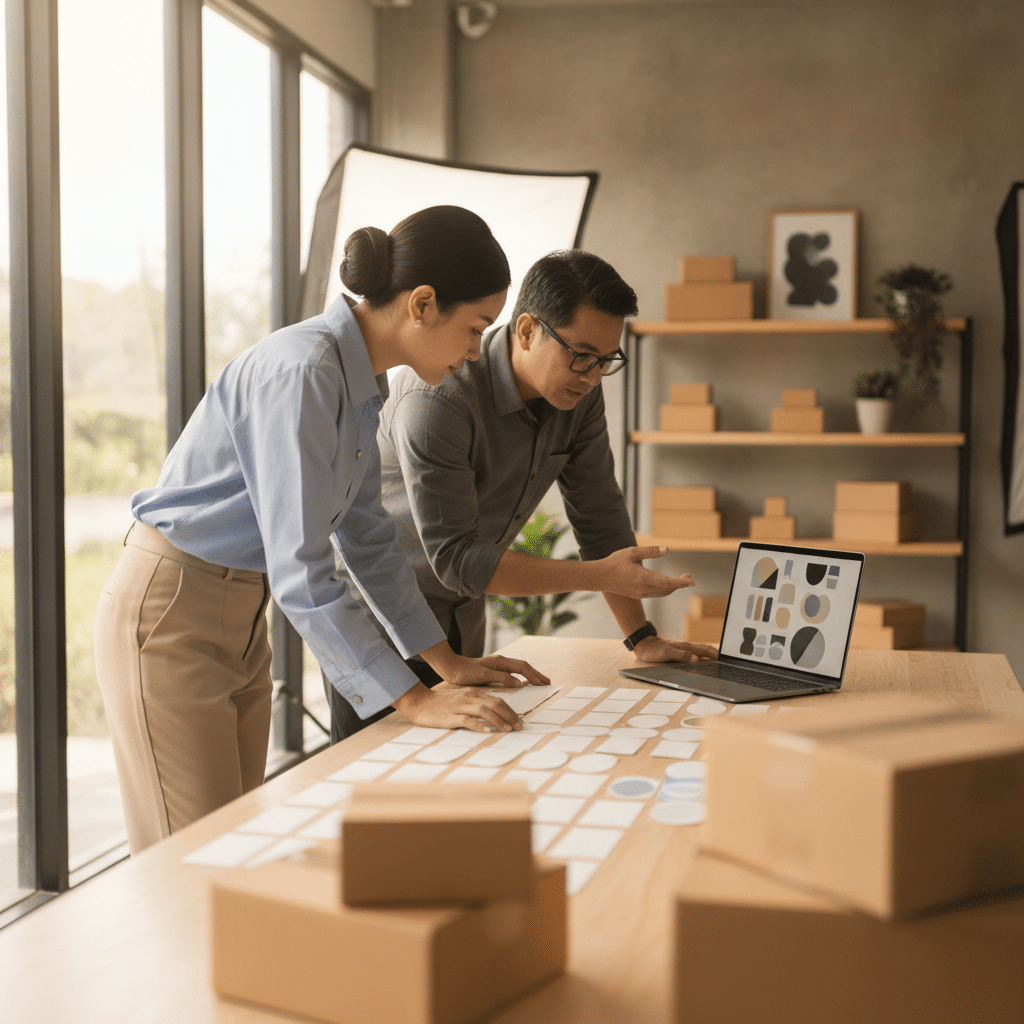
ทริคเลือกฟอนต์ฉลากสินค้า สะกดสายตา เพิ่มยอดขายปัง!
การเรียนรู้ทริคเลือกฟอนต์ฉลากสินค้า สะกดสายตา เพิ่มยอดขายปัง! เป็นมากกว่าการเลือกตัวอักษรที่สวยงาม แต่คือกลยุทธ์สำคัญในการสร้างแบรนด์และสื่อสารกับลูกค้าโดยตรง ฟอนต์ที่เหมาะสมสามารถสร้างความประทับใจแรกเห็น ดึงดูดความสนใจบนชั้นวางสินค้า และสื่อถึงคุณภาพและตัวตนของผลิตภัณฑ์ได้อย่างมีประสิทธิภาพ การเลือกฟอนต์จึงเป็นองค์ประกอบที่ผู้ประกอบการไม่ควรมองข้ามในการออกแบบฉลากสินค้าและบรรจุภัณฑ์
หัวใจสำคัญของการเลือกฟอนต์บนฉลากสินค้า
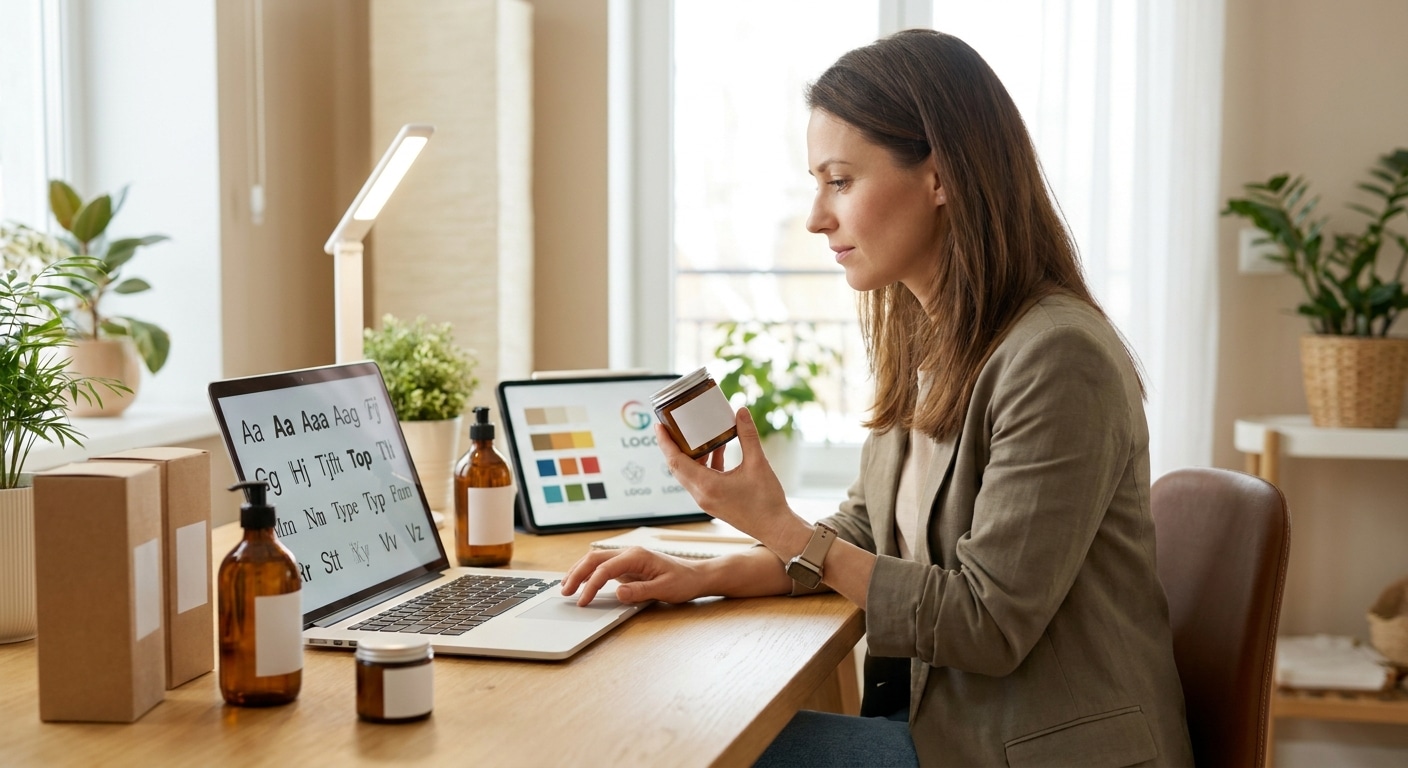
การเลือกฟอนต์สำหรับฉลากสินค้าที่มีประสิทธิภาพนั้นตั้งอยู่บนหลักการสำคัญที่ส่งผลโดยตรงต่อการรับรู้ของผู้บริโภคและการตัดสินใจซื้อ หลักการเหล่านี้ช่วยให้แน่ใจว่าฉลากไม่เพียงแต่สวยงาม แต่ยังทำหน้าที่สื่อสารได้อย่างสมบูรณ์
- ความชัดเจนในการอ่าน (Readability): ฟอนต์ต้องอ่านง่ายในทุกสถานการณ์ ไม่ว่าจะมองจากระยะไกล บนชั้นวาง หรือบนพื้นที่ขนาดเล็กของฉลาก ข้อมูลสำคัญ เช่น ชื่อสินค้า ส่วนประกอบ และวันหมดอายุ ต้องชัดเจนที่สุด
- การสะท้อนบุคลิกแบรนด์ (Brand Alignment): รูปแบบของฟอนต์ต้องสอดคล้องกับภาพลักษณ์ของแบรนด์ สินค้าพรีเมียมควรใช้ฟอนต์ที่ดูหรูหรา ในขณะที่สินค้าสำหรับเด็กควรใช้ฟอนต์ที่ดูสนุกสนานและเป็นมิตร
- ความเหมาะสมกับพื้นที่ (Space Suitability): การออกแบบต้องคำนึงถึงขนาดและรูปทรงของฉลาก ฟอนต์ที่เลือกต้องไม่ทำให้ฉลากดูอึดอัดหรือรกจนเกินไป และต้องจัดวางองค์ประกอบต่างๆ ได้อย่างลงตัว
- ความเรียบง่ายและเป็นระเบียบ (Simplicity): การใช้ฟอนต์จำนวนน้อยแบบ (ไม่เกิน 2-3 แบบ) จะช่วยให้ฉลากดูสะอาดตา เป็นมืออาชีพ และไม่สร้างความสับสนให้กับผู้บริโภค
ทำไมฟอนต์บนฉลากจึงมีผลต่อการตัดสินใจซื้อ
ในตลาดที่มีการแข่งขันสูง ฉลากสินค้าคือ “พนักงานขายเงียบ” ที่ทำงานตลอด 24 ชั่วโมง ฟอนต์ที่ใช้บนฉลากมีบทบาททางจิตวิทยาอย่างมากในการโน้มน้าวผู้บริโภค มันเป็นองค์ประกอบแรกๆ ที่สร้างการเชื่อมต่อทางอารมณ์และส่งผลต่อการรับรู้คุณค่าของผลิตภัณฑ์
การสื่อสารตัวตนของแบรนด์ในเสี้ยววินาที
ก่อนที่ลูกค้าจะได้อ่านข้อมูลทั้งหมดบนฉลาก พวกเขาจะรับรู้ถึง “ความรู้สึก” โดยรวมที่ฟอนต์สื่อออกมา ฟอนต์แบบ Sans-serif ที่เรียบง่ายและทันสมัยอาจสื่อถึงความน่าเชื่อถือ นวัตกรรม และความตรงไปตรงมา เหมาะสำหรับสินค้าเทคโนโลยีหรือผลิตภัณฑ์เพื่อสุขภาพ ในทางกลับกัน ฟอนต์แบบ Script ที่มีความโค้งมนสวยงามอาจสื่อถึงความหรูหรา ความเป็นงานฝีมือ หรือความเป็นธรรมชาติ เหมาะสำหรับสินค้าความงาม ไวน์ หรือสินค้าแฮนด์เมด การเลือกฟอนต์ที่ตรงกับแก่นแท้ของแบรนด์จะช่วยให้ลูกค้าเข้าใจตัวตนของสินค้าได้ทันทีและสร้างความรู้สึกเชื่อมโยงได้รวดเร็วยิ่งขึ้น
สร้างความน่าเชื่อถือและคุณภาพให้กับสินค้า
การออกแบบฉลากที่ดูเป็นมืออาชีพและอ่านง่ายจะสร้างความรู้สึกน่าเชื่อถือให้กับผู้บริโภค หากฉลากใช้ฟอนต์ที่อ่านยาก จัดวางไม่เป็นระเบียบ หรือดูไม่สอดคล้องกัน อาจทำให้ลูกค้ารู้สึกว่าผลิตภัณฑ์นั้นขาดความใส่ใจในรายละเอียดและอาจมีคุณภาพต่ำ การเลือกฟอนต์ที่เหมาะสมและการจัดวางองค์ประกอบอย่างมีหลักการจึงเป็นการลงทุนที่ช่วยยกระดับภาพลักษณ์ของสินค้าให้ดูมีคุณภาพและน่าไว้วางใจ ซึ่งเป็นปัจจัยสำคัญที่นำไปสู่การตัดสินใจซื้อในที่สุด
หลักการพื้นฐาน: เลือกฟอนต์อย่างไรให้ตอบโจทย์
การเลือกฟอนต์สำหรับฉลากสินค้าไม่ใช่เรื่องของความชอบส่วนตัว แต่เป็นกระบวนการที่ต้องอาศัยความเข้าใจในหลักการออกแบบและการสื่อสาร เพื่อให้ได้ผลลัพธ์ที่สามารถดึงดูดลูกค้าและสร้างยอดขายได้จริง
ความชัดเจนต้องมาก่อนความสวยงาม (Readability First)
หน้าที่หลักของข้อความบนฉลากคือการให้ข้อมูล ฟอนต์ที่สวยงามแต่ซับซ้อนจนอ่านยากอาจทำให้ลูกค้าพลาดข้อมูลสำคัญ เช่น คำเตือนการแพ้ ส่วนประกอบหลัก หรือวิธีการใช้งาน ซึ่งอาจส่งผลเสียต่อการตัดสินใจซื้อและประสบการณ์หลังการใช้งาน ควรทดสอบฟอนต์ในขนาดต่างๆ ที่จะใช้จริงบนฉลากเพื่อให้แน่ใจว่าสามารถอ่านได้อย่างชัดเจน แม้ในกลุ่มผู้บริโภคที่มีปัญหาสายตาหรือเมื่อมองผ่านๆ บนชั้นวางสินค้า
ความสอดคล้องกับบุคลิกของแบรนด์ (Brand Personality)
ฟอนต์เปรียบเสมือน “น้ำเสียง” ของแบรนด์ การเลือกใช้ฟอนต์จึงต้องสะท้อนบุคลิกที่แบรนด์ต้องการสื่อสารออกไปอย่างถูกต้อง
- แบรนด์หรูหรา/พรีเมียม: มักนิยมใช้ฟอนต์ประเภท Serif ที่มีเชิง ซึ่งให้ความรู้สึกคลาสสิก สง่างาม และน่าเชื่อถือ หรือฟอนต์ Sans-serif ที่บางและเรียบง่ายเพื่อสื่อถึงความมินิมอลและทันสมัย
- แบรนด์สำหรับเด็ก/ครอบครัว: เหมาะกับฟอนต์ที่มีความโค้งมน ดูเป็นมิตร สนุกสนาน และเข้าถึงง่าย อาจเป็นฟอนต์ลายมือที่ไม่เป็นทางการจนเกินไป
- แบรนด์ธรรมชาติ/ออร์แกนิก: มักใช้ฟอนต์ที่ให้ความรู้สึกสบายๆ เหมือนเขียนด้วยมือ หรือฟอนต์ Serif ที่ดูเรียบง่าย เพื่อสื่อถึงความเป็นธรรมชาติและความจริงใจ
- แบรนด์ทันสมัย/เทคโนโลยี: ฟอนต์ Sans-serif ที่มีความสะอาดตาและรูปทรงเรขาคณิตเป็นตัวเลือกที่ยอดเยี่ยมในการสื่อถึงนวัตกรรม ความแม่นยำ และความเป็นปัจจุบัน
ความเรียบง่ายคือกุญแจสำคัญ (Simplicity is Key)
การพยายามใช้ฟอนต์หลายรูปแบบบนฉลากขนาดเล็กมักจะให้ผลลัพธ์ที่ตรงกันข้ามกับที่คาดหวัง คือทำให้ดูรกและไม่เป็นมืออาชีพ กฎทั่วไปคือการจำกัดการใช้ฟอนต์ไว้ที่ไม่เกิน 2-3 รูปแบบ โดยอาจแบ่งเป็นการใช้งานดังนี้:
- ฟอนต์หลัก (Primary Font): ใช้สำหรับชื่อแบรนด์หรือชื่อสินค้าที่ต้องการให้โดดเด่นที่สุด
- ฟอนต์รอง (Secondary Font): ใช้สำหรับหัวข้อย่อยหรือคำอธิบายสั้นๆ ควรเป็นฟอนต์ที่เข้ากันได้ดีกับฟอนต์หลักแต่อาจมีความแตกต่างเล็กน้อยเพื่อสร้างคอนทราสต์